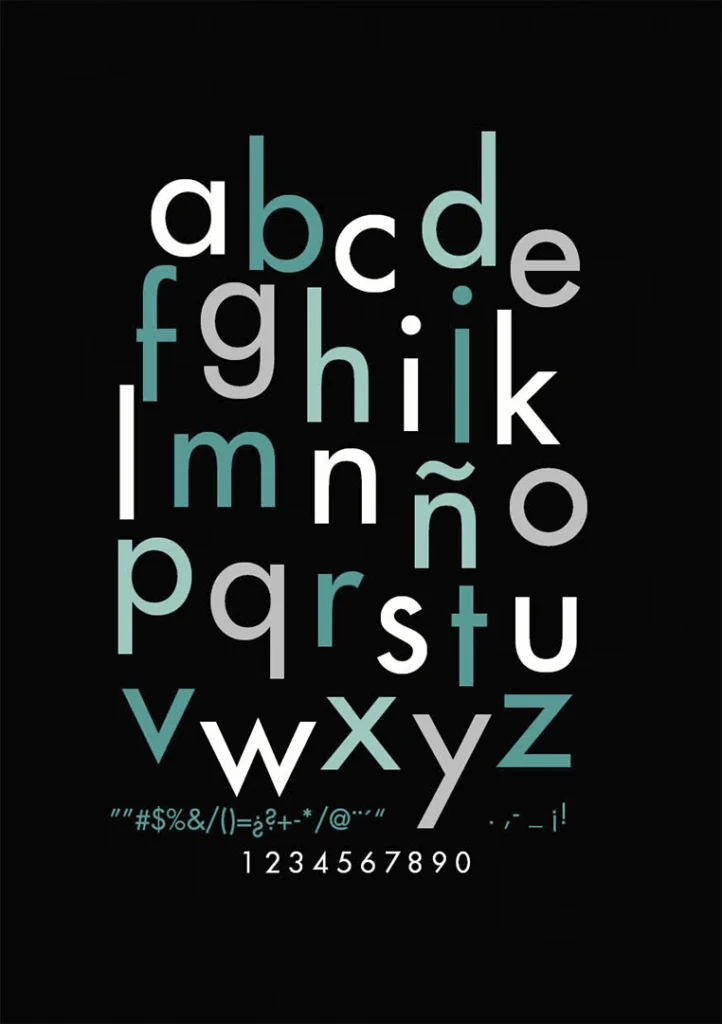
Futura es una sans serif geométrica diseñada por Paul Renner entre 1924 y 1926 y lanzada comercialmente en 1927-1930. Con la Futura, en términos tipográficos, la revolución industrial había llegado a su conclusión lógica: máxima simplicidad y formas geométricas. Inicialmente, la fundición Bauer emitió Futura en seis pesos, una versión condensada en tres pesos y una Inline.